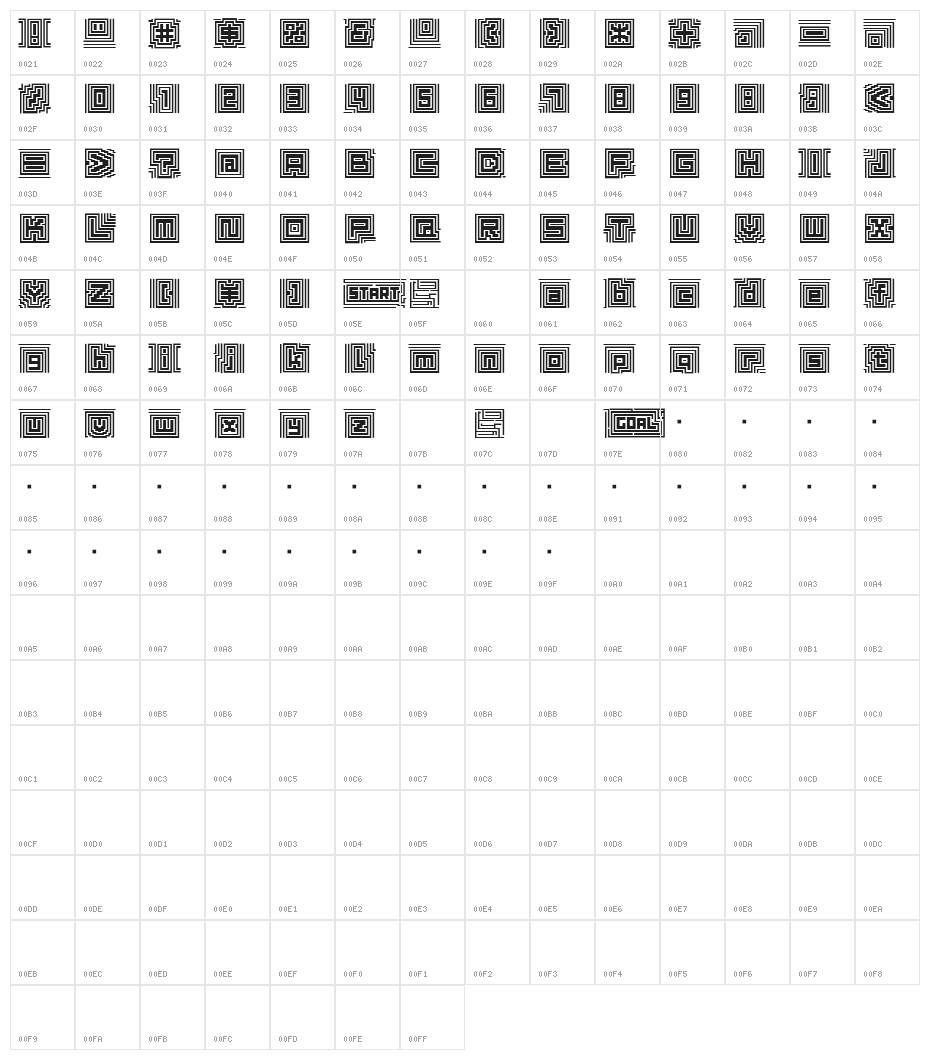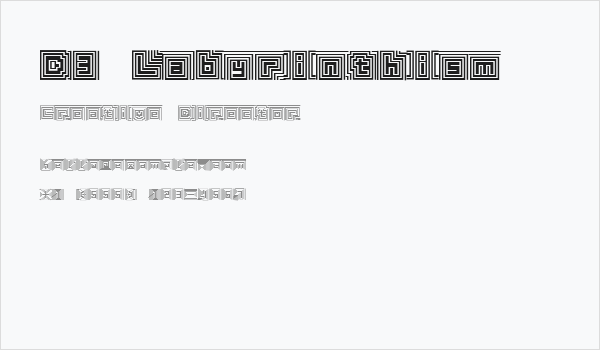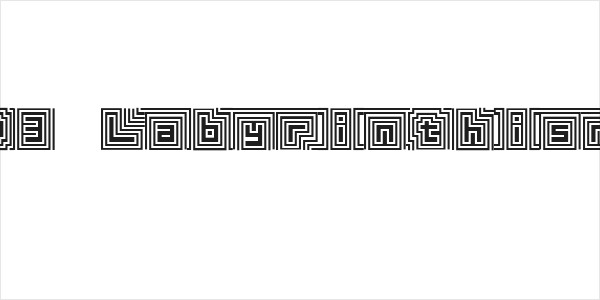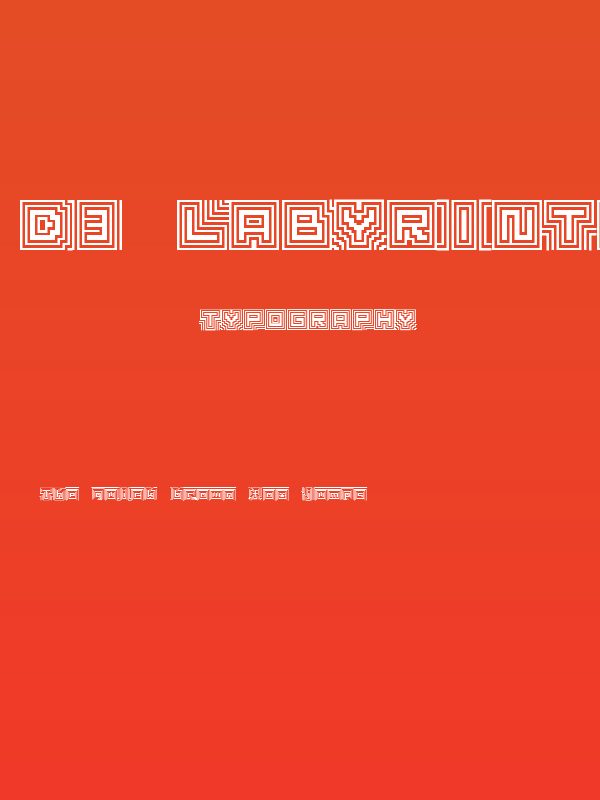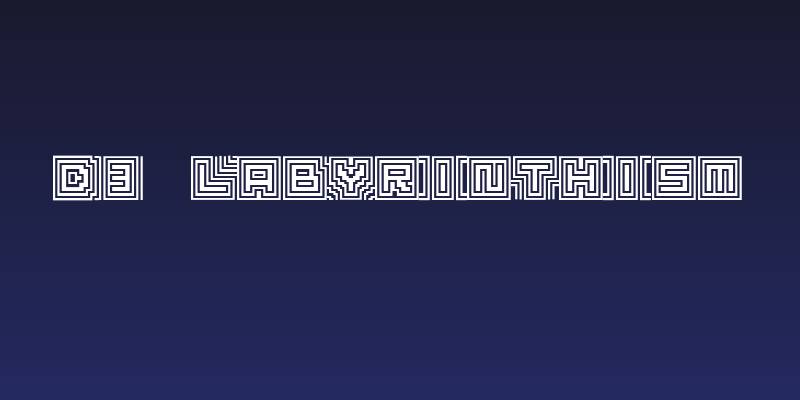
D3 Labyrinthism Font
| Proyectos propuestos | Ideal for posters, album covers, video game titles, and branding that requires a bold, artistic touch. |